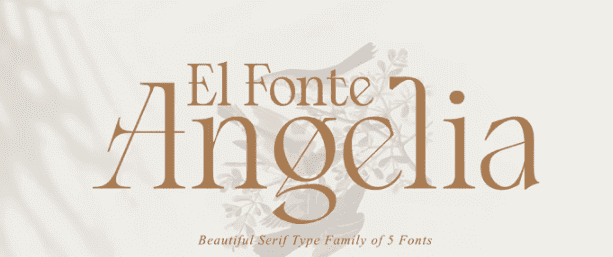
Название: El Fonte Angelia Font (2022)
Представляем новый шрифт " El Fonte Angelia " Прекрасное семейство шрифтов с засечками вдохновлено шрифтами с засечками, которые использовались в редакционных СМИ в 70-х и 80-х годах. Такие мягкие и нежные формы, как в шрифте Cooper или плавные, наклонные штрихи в шрифте Windsor, объединены в единый дизайн, который имеет знакомые, свежие и современные вкусы.
Созданный с учетом природных особенностей, он создает ощущение естественной мягкости и выразительности. Мы продвинули концепцию в направлении, ориентированном на удобство использования, чтобы работать как смелый инструмент и красивый коммуникатор.
Переменная El Fonte Angelia обеспечивает плавность дизайна в 5 весовых категориях.
Шрифт расширяет сферу своего использования, предлагая варианты начертания от Light до Bold. Естественные изгибы, выпуклости и наклонные стволы приобретают все больший характер по мере того, как шрифт набирает вес. В то время как в более тонких начертаниях снижается контрастность и применяются оптические коррекции для создания теплого и нежного вида.
Набор символов El Fonte Angelia включает в себя дополнительные символы, стилистические альтернативы, уникальные лигатуры и пунктуацию с учетом регистра, создавая стабильное семейство рабочих лошадок, готовых к реализации проектов любого размера. При большом размере кегля вы можете оценить формы букв, в то время как та же сдержанность и сосредоточенность создают ровную текстуру при малом размере кегля и длительном чтении.
Разнообразие весовых категорий обеспечивает широкий выбор, который поможет вам найти наилучший типографский цвет для вашего проекта. Более легкие веса хорошо подходят для основного текста, а более тяжелые - для заголовков с высокой степенью воздействия. Доступные стилистические альтернативы предлагают множество различных символов, которые придадут вашему логотипу или визитной карточке уникальный вид.